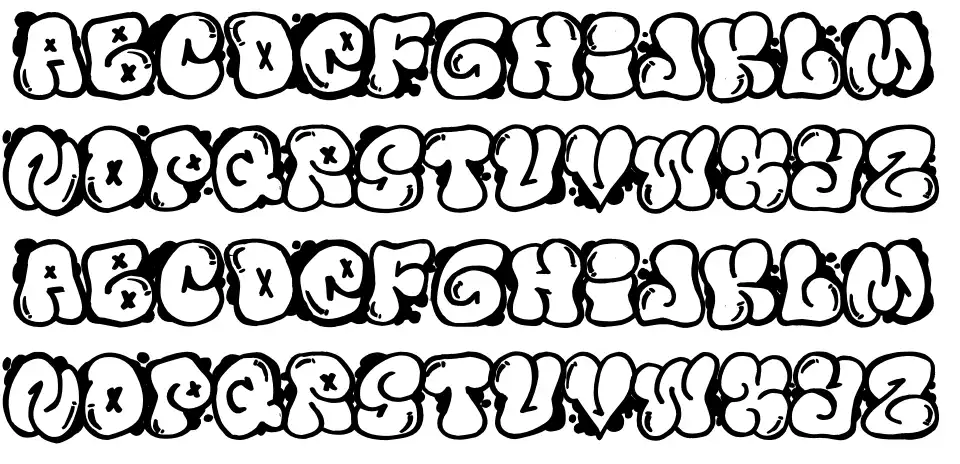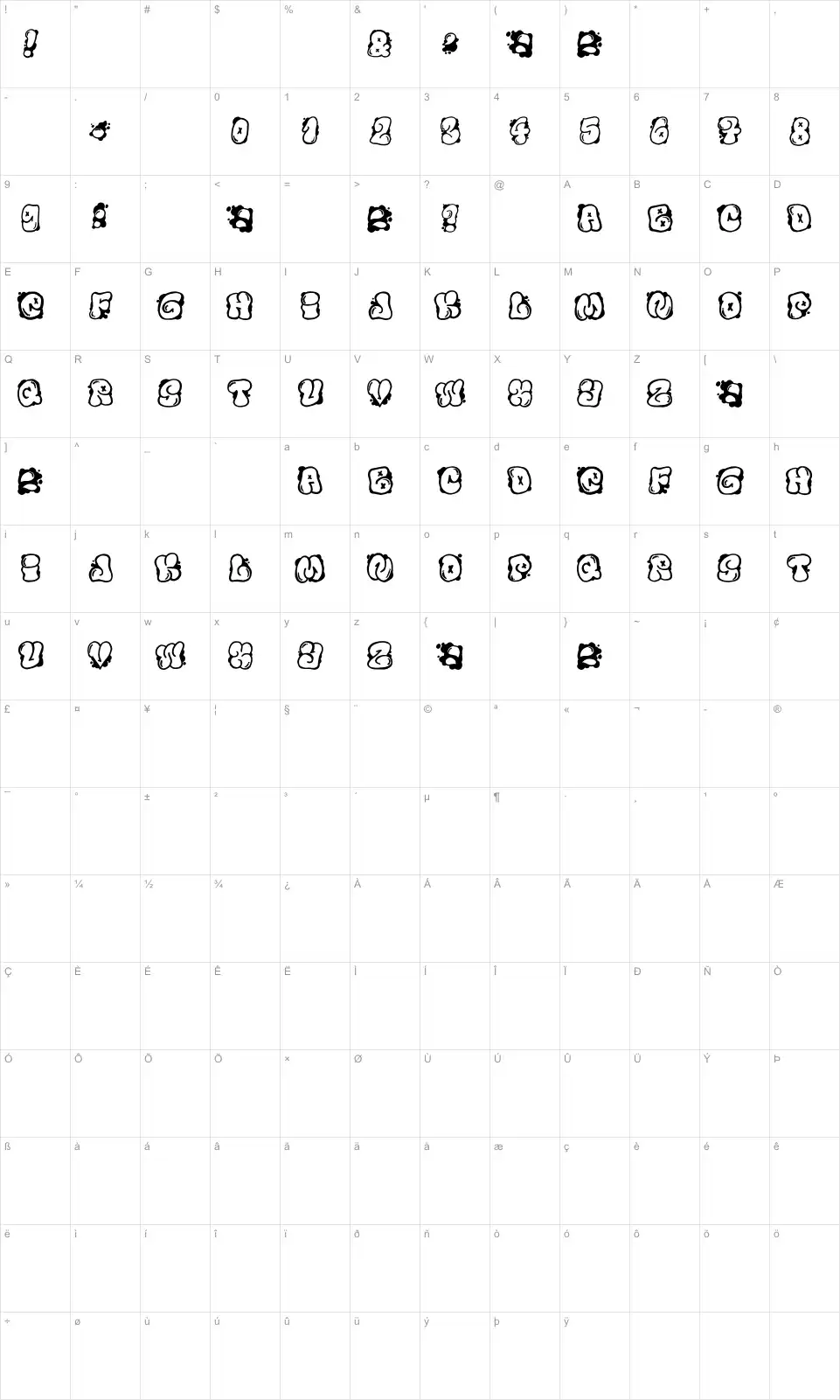
A fonte El&Font Bubble, criada pelo designer Jérôme Delage, é perfeita para quem busca uma fonte script com um toque de graffiti. Esta fonte pertence à categoria de Script e é caracterizada pelo seu estilo descontraído e vibrante. Se você está procurando por uma fonte que traga vida e personalidade a seu design, El&Font Bubble é uma escolha ótima. Para aqueles que desejam experimentar o design da fonte antes de usá-la, é possível gerar uma pré-visualização de texto personalizada online. El&Font Bubble está disponível em formato TTF e é gratuita para uso pessoal. Adicionada em 12 de julho de 2022, esta fonte já foi baixada mais de 122.849 vezes, demonstrando sua popularidade. Com um tamanho de 30 KB, El&Font Bubble é uma excelente escolha para quem procura uma fonte script leve e versátil.
Categoria: Script › Graffiti
Designer: Jérôme Delage